Neue Berliner Font Foundry »Show Me Fonts« gestartet
Anfang Oktober ist die neue Font Foundry von Bernd Volmer offiziell gestartet. »Show Me Fonts« soll nicht nur als Schriftvertrieb dienen, sondern auch zu einer dynamischen Plattform werden, um charaktervolle und vielseitige Schriften zu bieten.
Bernd Volmer hat bereits in Unternehmen wie FontShop, Monotype und HvD Fonts Erfahrungen in Schrifttechnik, Schriftgestaltung und Projektmanagement sammeln können. Er arbeitete unter anderem an Projekten wie »Berlin Type« (offizielle Schriftfamilie der Stadt Berlin) und »TeleNeo« (neue Markenschriftart der Telekom). Mit der eigenen Foundry Show Me Fonts hat sich der Designer nun einen langgehegten Traum erfüllt.
Zur Veröffentlichung bei der neuen Typefoundry sind Premium-Display-Schriften für Branding, Poster und Packaging und sorgfältig ausgearbeitete Textschriften geplant. Der Schwerpunkt liegt auf charaktervollen Schriftarten. Freunde und Kollegen von Bernd Volmer sollen ebenfalls auf der Plattform ihre kreativen Energien bündeln können, um Kreative, Agenturen und Firmen mit frischen Schriften zu beliefern.
Ein Blick auf das Schriften-Portfolio von »Show Me Font«
Bereits jetzt sind bei der Berliner Typefoundry eine Auswahl an vielfältigen Schriftfamilien am Start. Hier eine kurze Übersicht:
Capellini
Inspiriert von der Mode, bricht diese Schrift teilweise mit dem Klischee einer klassizistischen linear Antiqua. Sie ist variabel und eignet sich unter anderem für Logos, Poster und Branding.
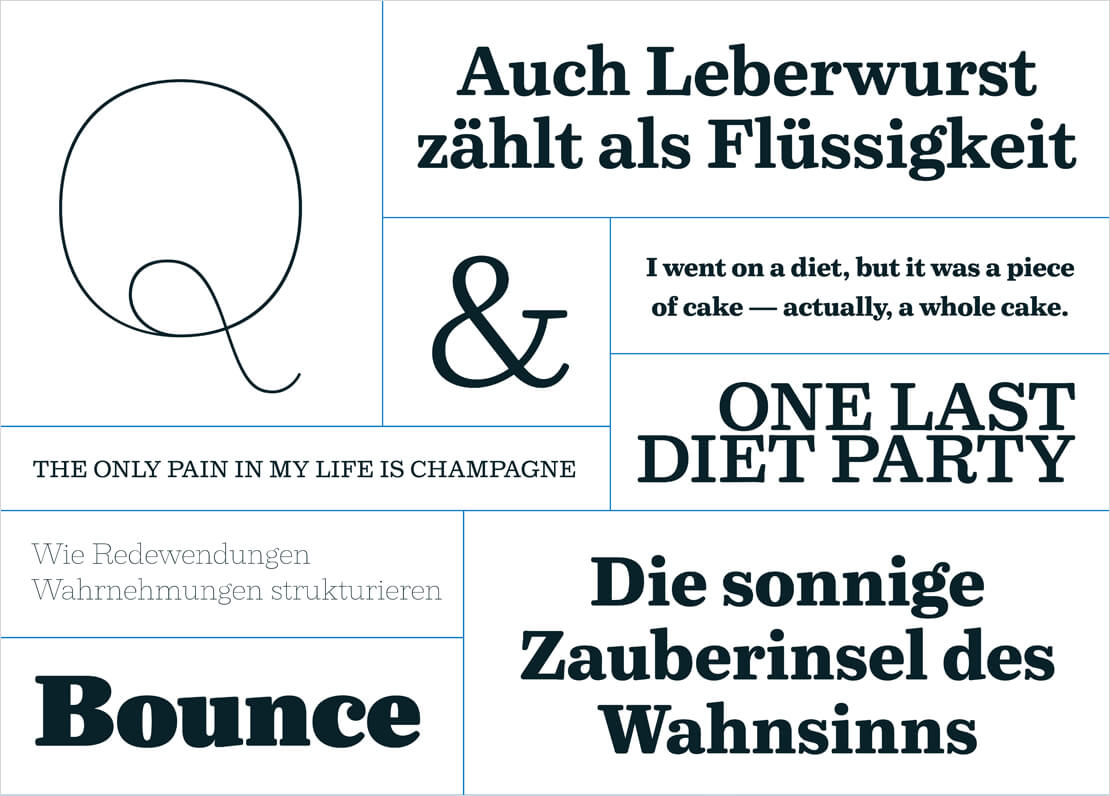
Chauncey
Eine zeitgenössische Neuinterpretation der Legibility Group Bleisatzschriften der 1930er Jahre. Sie bietet sowohl Display-Merkmale als auch entsprechende Textqualitäten.
Petrosian Mono
Eine Monospace Schrift, die sowohl für Code-Editoren, ASCII-Art etc. als auch in größeren Größen geeignet ist. Sie fällt durch ihre markanten Eigenheiten aus.
Seraphs
»Seraphs« ists eine variable Schriftfamilie, die zwischen verschiedenen Serifenstilen interpoliert. Sie kann beispielsweise als Prototyping-Werkzeug für Kreative dienen, um verschiedene Designrichtungen zu erkunden und mit einer Schrift zu experimentieren.
Weekend Grotesk
Diese Schriftart stellt eine kompromisslose Display-Schriftfamilie dar, die mit ihrem übertriebenen Charakter zudem auch eine gewisse Urlaubsstimmung ausstrahlt. Der primäre Fokus liegt auf Branding mit Wiedererkennbarkeit.
Ausblick
»Show Me Fonts« plant, das Portfolio mit Schriftarten zu erweitern, die durch Kreativität und Designexzellenz überzeugen. Qualität in Design und Technologie sollen dabei im Vordergrund stehen.